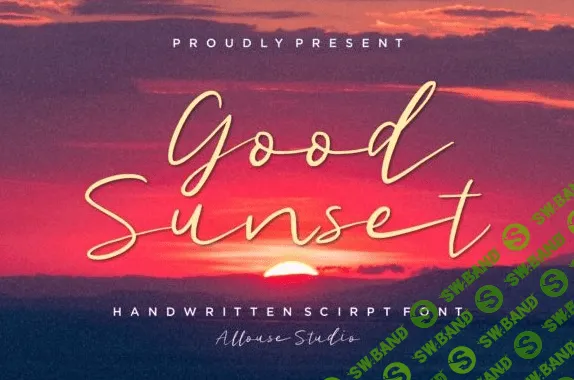
Название: Good Sunset Font
Красивый закат - тонкий и элегантный рукописный шрифт.
Он прекрасно смотрится на различных дизайнах, требующих индивидуального стиля, таких как свадебные приглашения, благодарственные открытки, свадьбы, поздравительные открытки, логотипы и так далее.